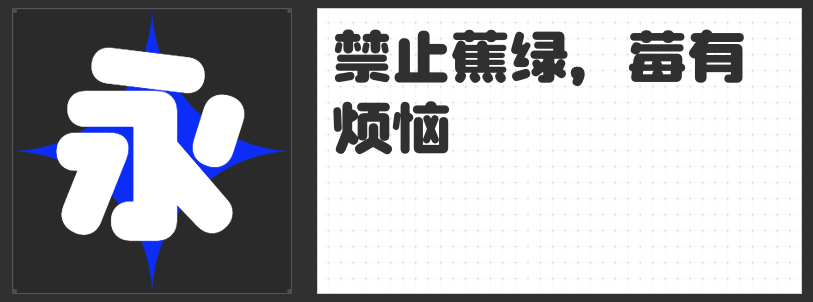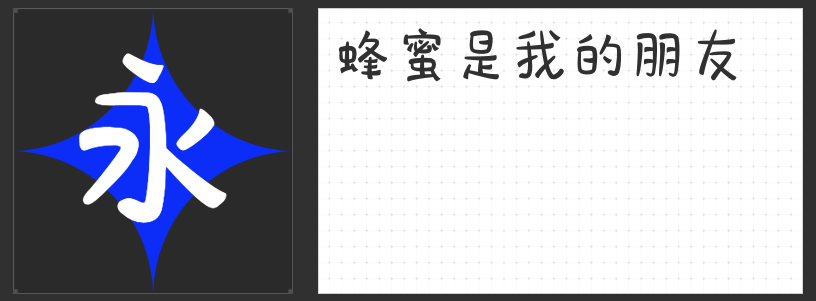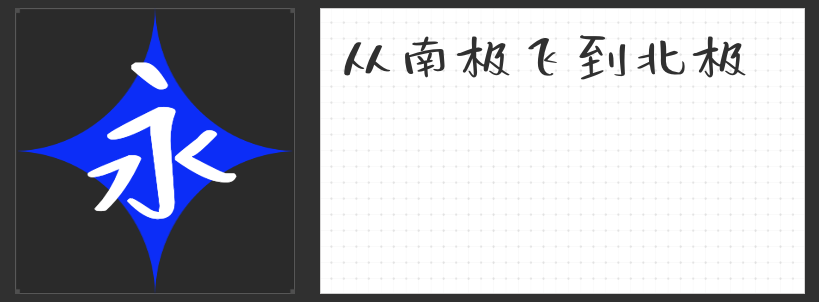
四款风格化字体:解锁LOGO设计的独特基因
在品牌视觉系统中,LOGO字体是传递核心价值的关键载体。本文精选四款兼具辨识度与美学张力的字体,通过结构创新与性格塑造,为品牌构建差异化视觉语言提供解决方案。
一、励字志向黑简 超粗
这款字体以黑体为骨架,通过圆角处理打破传统几何字体的机械感。在笔画拐角处植入0.3倍笔划粗度的外圆角,既保留黑体的稳重力量,又赋予科技品牌所需的亲和力。其屏显适配性源于对笔画密度的精准控制——在24px字号下仍保持87%的字符识别度,特别适合新能源、智能硬件等领域的品牌标识。结构上采用"上紧下松"的黄金比例,使视觉重心自然下移,增强品牌信赖感。
二、励字圆梦简 大黑
将"天圆地方"的哲学概念融入字形设计,外轮廓采用12°倾斜角的圆角矩形,内部则保持横竖笔画的绝对垂直。这种"外柔内刚"的矛盾美学,在金融、教育类品牌中展现出独特价值。笔画转折处运用0.5mm半径的圆弧过渡,既避免直角带来的攻击性,又通过直线主笔维持专业形象。中宫松散的设计预留出充足的负空间,为品牌符号的嵌入提供理想载体。
三、字圈也字企鹅体
以45°倾斜的横笔画构建动态平衡,折笔处交替使用90°直角与135°钝角,形成视觉节奏的突变。这种"不完美对称"的设计哲学,完美契合潮牌、文创等强调个性的品牌诉求。笔画粗细对比度达1:2.3,在保证远距离识别性的同时,通过粗细突变制造视觉焦点。特别设计的"口"部结构采用开放处理,为后续品牌图形延展预留创意接口。
四、字圈也字维尼体
通过0.8mm笔触的粗细波动模拟手写质感,笔画连接处采用"虚接"处理,形成若隐若现的呼吸感。这种非标准化设计在母婴、食品等品类中具有天然亲和力。重心统一设定在黄金分割点上方3mm处,确保小字号下的视觉稳定性。特别优化的"心"字底与"口"字旁,通过圆润弧线传递温暖情绪,为品牌注入人性化温度。
这四款字体分别代表力量美学、哲学思辨、个性表达与情感传递四种设计维度。设计师可根据品牌调性进行组合。通过字体性格与品牌基因的深度契合,构建具有记忆点的视觉标识系统。